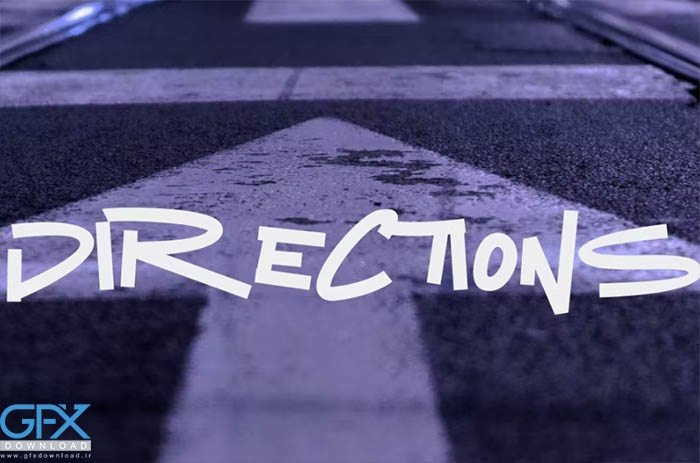
فونت انگلیسی Micks Street
فونت میکس استریت Micks Street یک فونت انگلیسی مدرن و معتبر است. مناسب برای نیازهای حرفه ای و برندینگ یک محصول. این فونت رایگان برای هر پروژه برندسازی مانند نقل قول، لوگو، هدر وبلاگ، پوستر، نواربندی، نامه، دعوت نامه، لوازم التحریر و غیره مناسب است. طیف گسترده ای از زمینه ها. برای دانلود رایگان فونت Micks Street از جی اف ایکس دانلود به ادامه مطلب مراجعه کنید.
• حروف بزرگ
• حروف کوچک